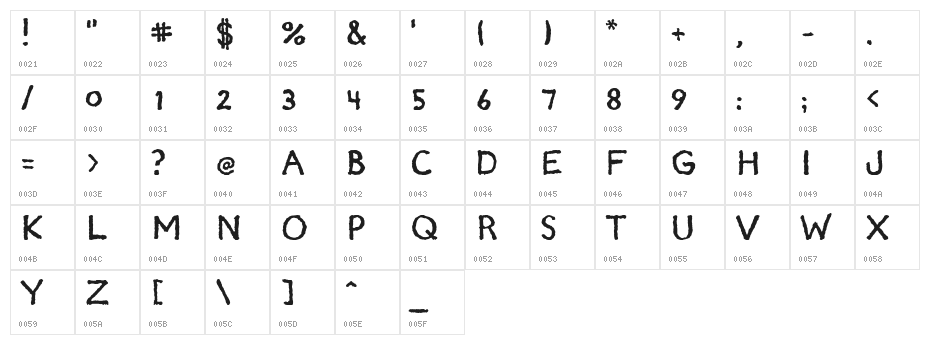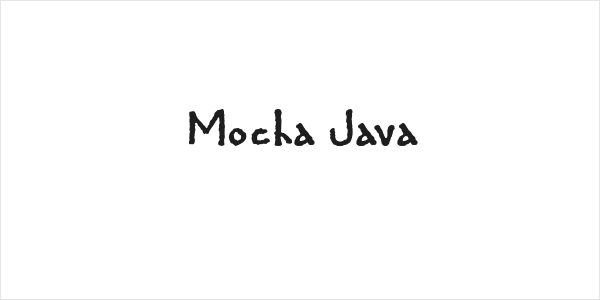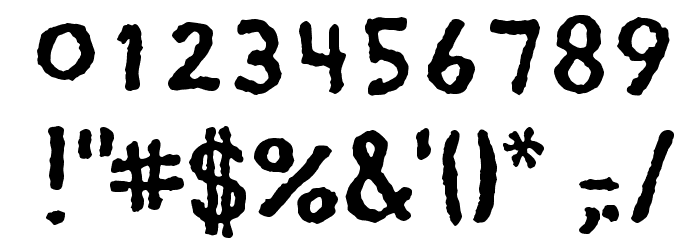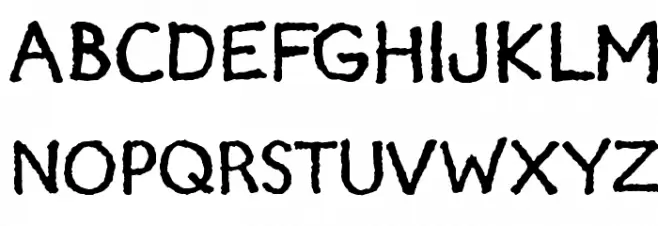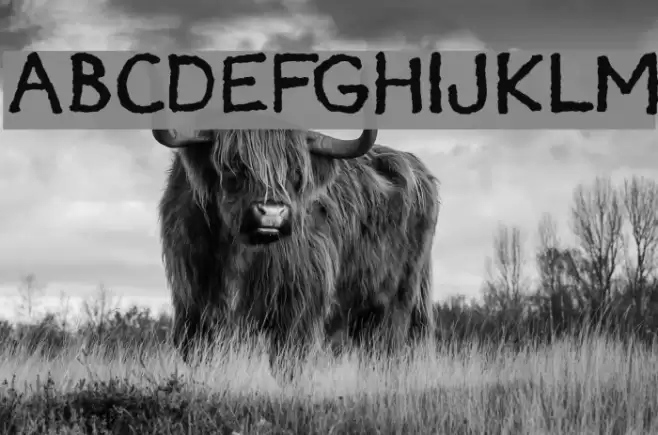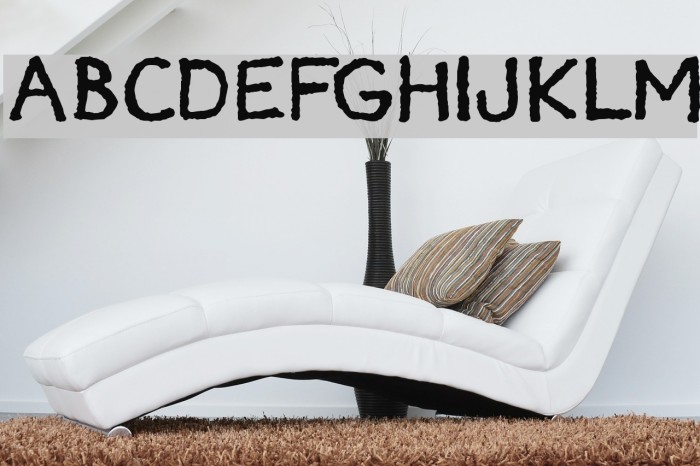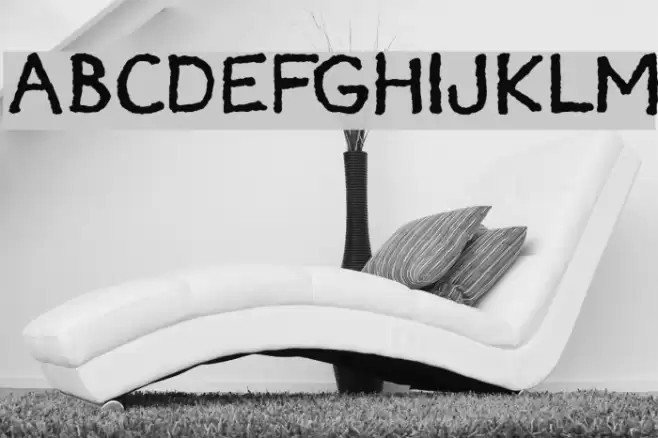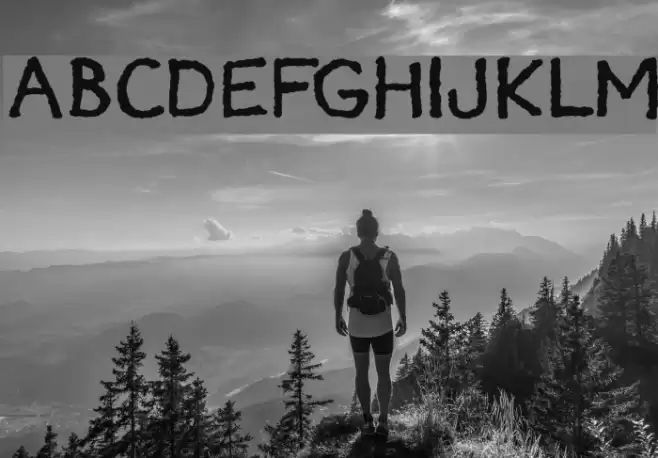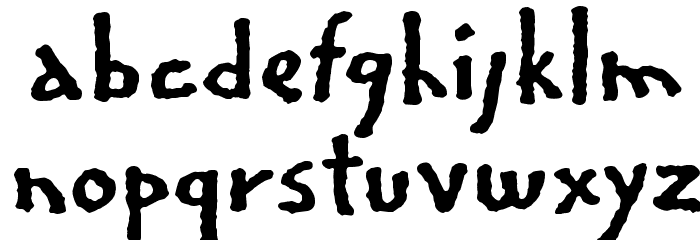
Mocha Java Font
| Style général | Casual, Playful |
| Cas d'utilisation | Headlines, Informal text, Creative projects |
| Projets proposés | Ideal for greeting cards, children's books, casual branding, and creative projects that require a personal touch. |